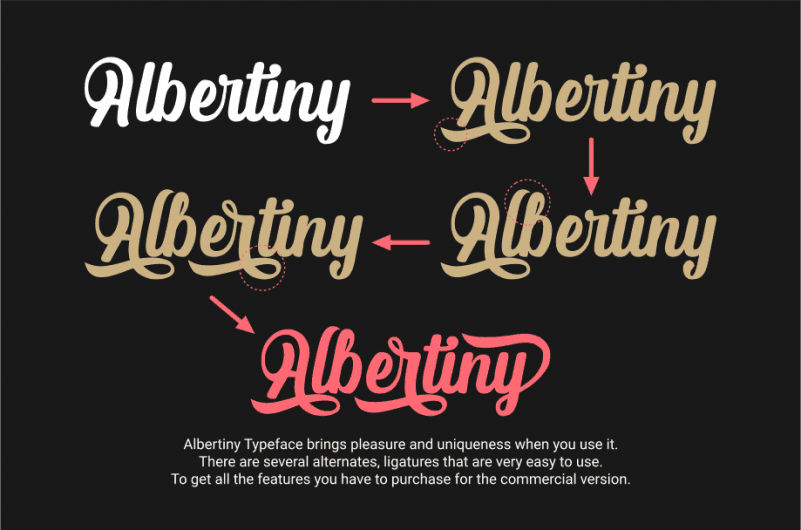
Albertiny Calligraphy Font – Download Grátis
A fonte Albertiny Calligraphy é uma criação elegante que resulta da harmoniosa mistura entre um pincel e uma escova para escrever a mão, proporcionando um aspecto encantador e autêntico. Suas linhas fluidas e delicadas têm o poder de transformar qualquer projeto DIY em algo encantador e único. Esta fonte escrita a mão é perfeita para quem deseja dar vida a seus projetos casuais, seja na decoração da casa ou em trabalhos manuais. Com Albertiny Calligraphy, cada detalhe ganha um toque de charme e personalidade.